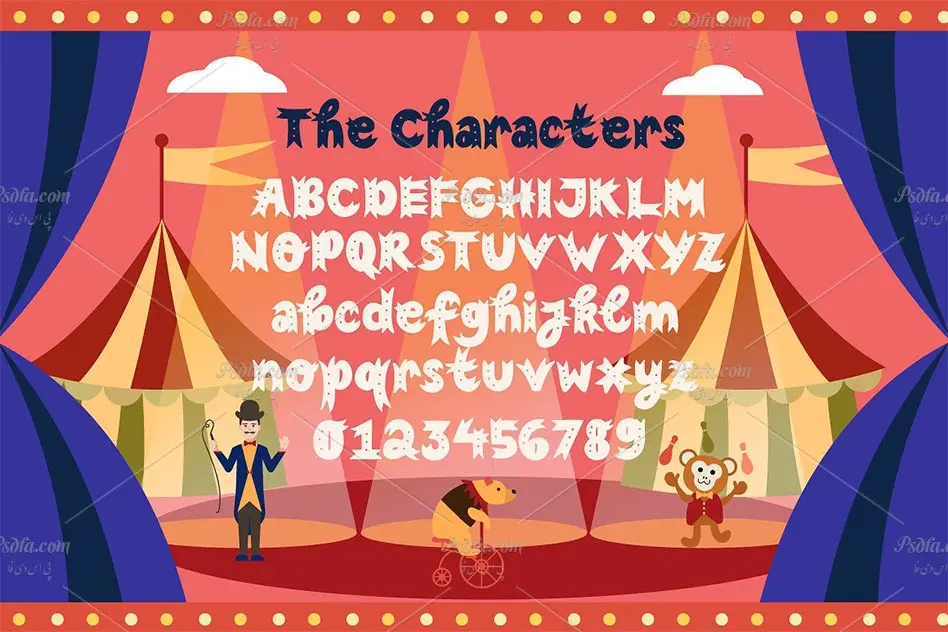
فونت انگلیسی فانتزی و کارتونی سیرک بزرگ The Great Circus Font
فونت انگلیسی فانتزی و کارتونی
در این مطلب شاهد فونت انگلیسی فانتزی و کارتونی سیرک بزرگ The Great Circus مناسب جهت استفاده در طرح های گرافیکی می باشید. این فونت زیبا در قالب فرمت های ttf , otf , eot , svg , woff و woff2 در سایت بارگذاری شده اند که با نصب فایل ttf یا otf در پوشه فونت های سیستم قادر به استفاده از آن در تمام نرم افزار گرافیکی و ویرایشگر متن می باشید. همچنین از دیگر فرمت های موجود می توان در طراحی صفحات وب نیز استفاده نمود. این فونت زیبا در سه وزن و سبک معمولی ، توخالی و ضخیم طراحی شده است که به کمک آن ها می توانید طرح های زیبا ، فانتزی و کودکانه خلق کنید.
- نام فونت : The Great Circus
- وزن : معمولی ، توخالی و ضخیم